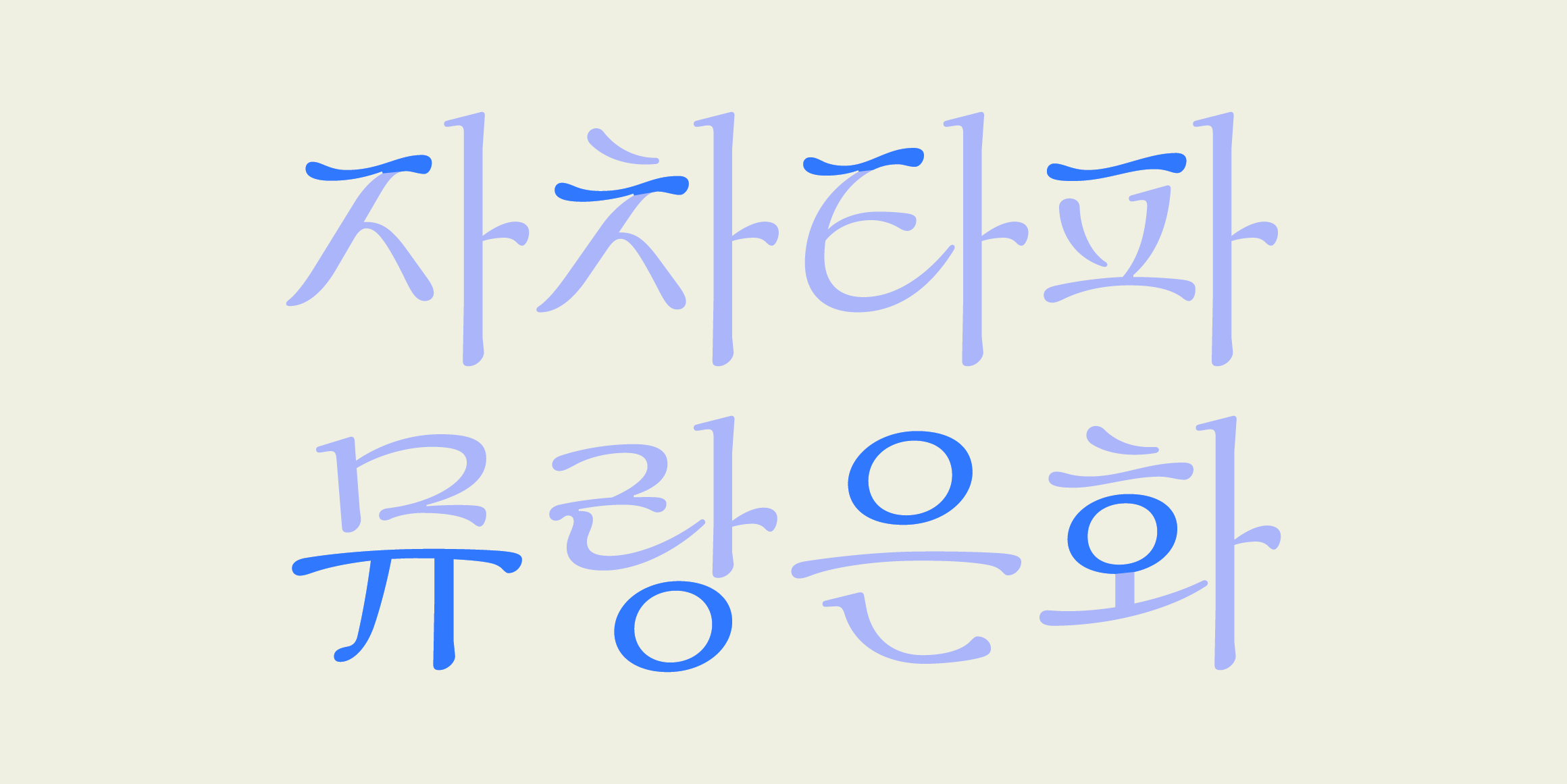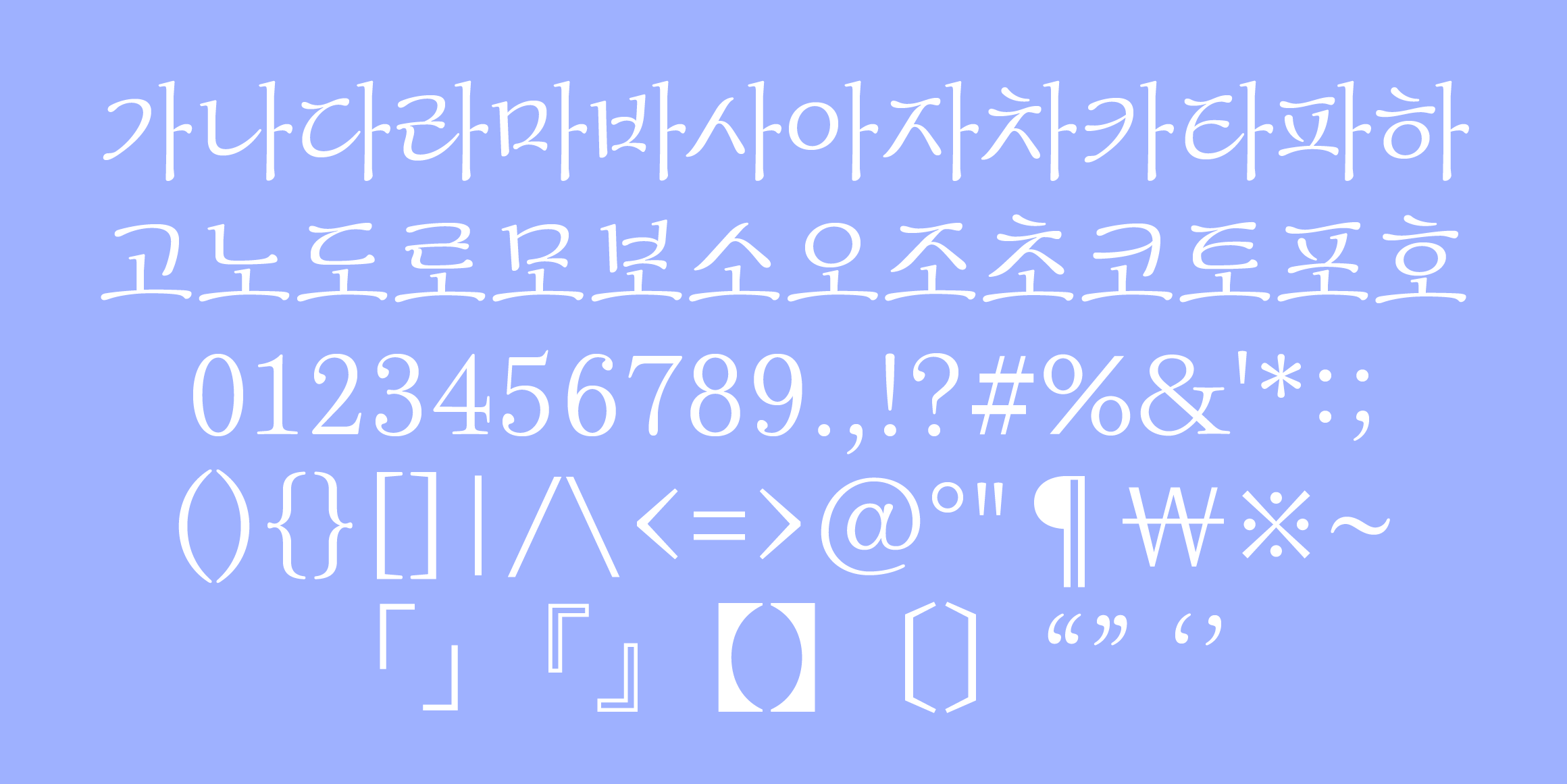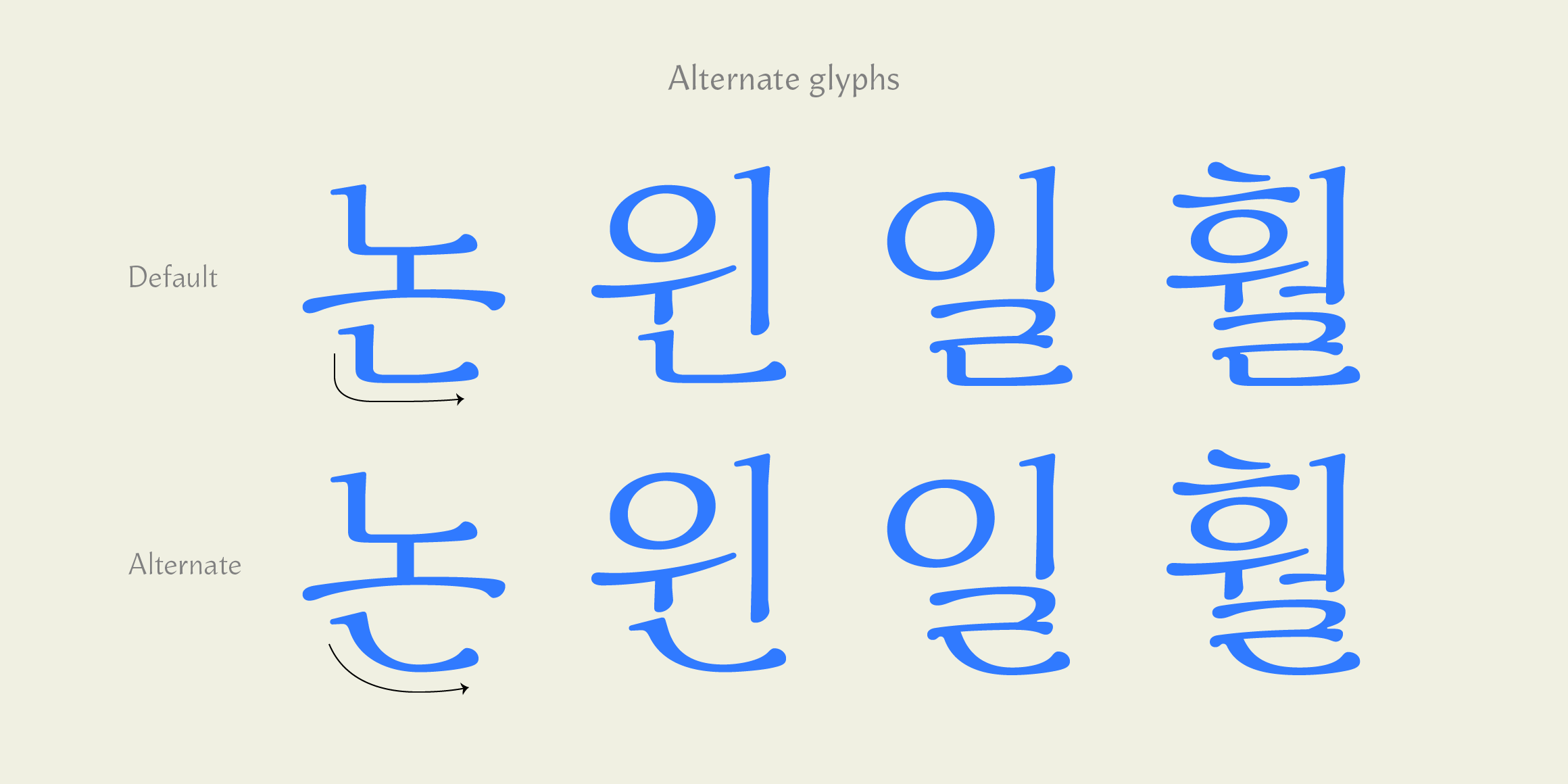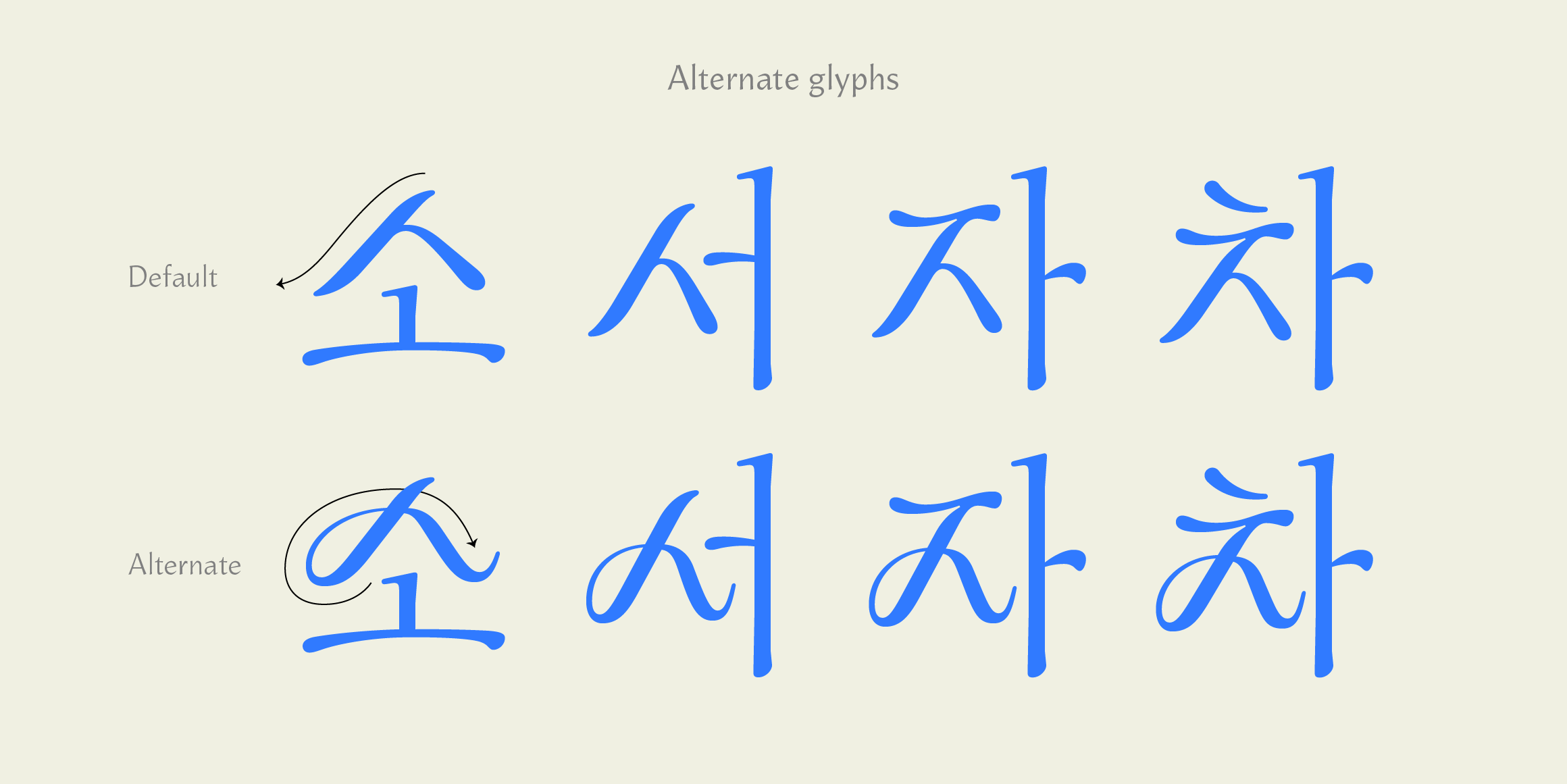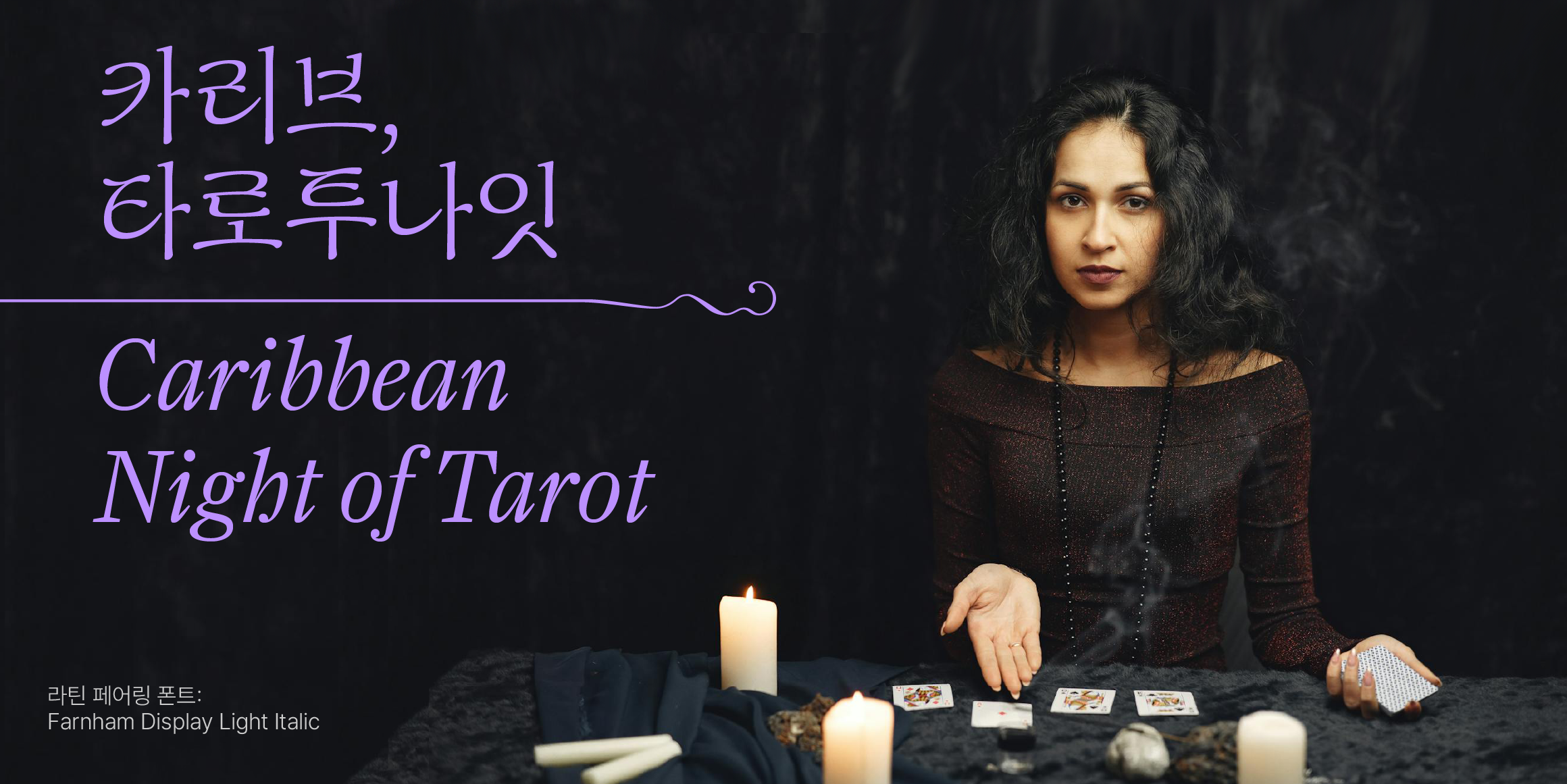
그리스 로마 신화 속 여신인 뮤즈가 부르는 노래처럼 유연하고 부드러운 흐름이 느껴지도록 만들었습니다. 곡선 적인 획과 부리, 부드러운 자소 형태에서 우아함을 연상할 수 있도록 표현했습니다. 비교적 제목용 사이즈에서 개성있는 표현이 돋보이는 폰트 입니다. 라틴 알파벳에서 세리프 스타일 혹은 유려한 필기감이 돋보이는 폰트와 페어링했을 때 어울릴 수 있는 한글 폰트 입니다.
일부 글꼴에서 대체 글리프를 지원합니다.
오픈타입 피처 스타일 세트를 사용하면 곡선감이 풍부한 스타일로 변경할 수 있습니다.
‘초성 ㅅ,ㅈ,ㅊ 스타일 대체’는 다른 스타일 세트와 함께 사용할 수 없으니 단독으로 사용해 주세요. ‘초성 ㅅ,ㅈ,ㅊ 스타일 대체’는 복잡도가 높은 ㅐ꼴받친글자와 혼합모임꼴에서는 지원하지 않습니다. 아래 사용 가능 글자를 확인해주세요.
• 초성 ㅅㅈㅊ 스타일 대체 (Chosung siot stylistic set)
• 종성 ㄴ 스타일 대체 (Jongsung nieun stylistic set)
• 종성 ㄹ 스타일 대체 (Jongsung rieul stylistic set)